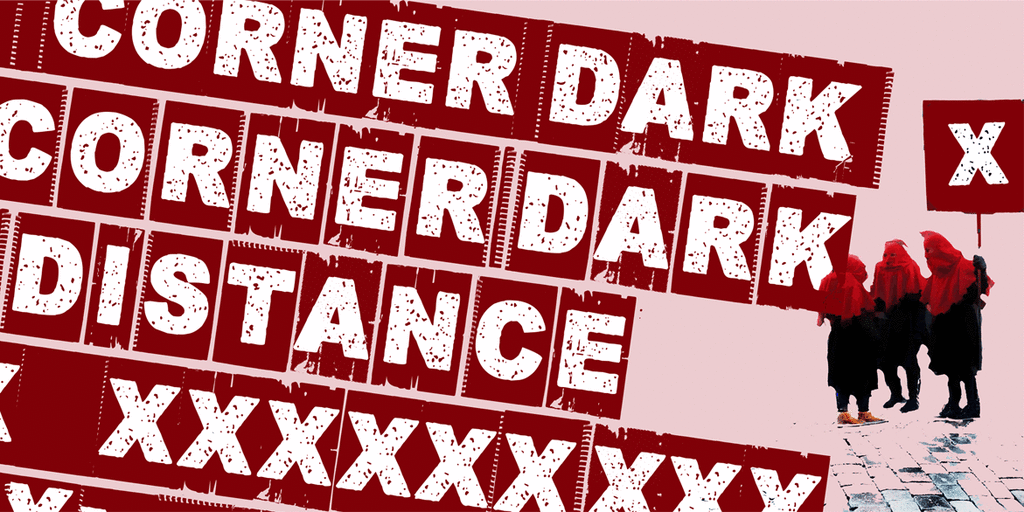
A Fonte Corner Dark é uma família única de fontes decorativas criada pelo designer Hamilton. Essa família de fontes oferece um estilo único que se destaca no ambiente digital, proporcionando um toque especial aos projetos digitais e impressos. Com seu design elegante e sofisticado, a Corner Dark está ideal para adicionar um toque diferenciado em elementos gráficos como nomes de produtos, logotipos ou banners de web. Se você procura uma fonte que destaca-se na tela do computador ou no papel, esta é certamente uma opção. A Hamilton oferece seu trabalho de forma transparente e amigável: as fontes são gratuitas para uso pessoal, mas para uso comercial, como por exemplo em projetos publicitários ou impressão, pode ser necessário adquirir um licença. Para isso, o designer solicita uma contribuição mensal de 15€ (em Euros) ou $20 (Dólares), através do PayPal. Mas não se preocupe, a Hamilton também recebe donativos regulares de seus seguidores e apreciadores da arte da grafia. Essa flexibilidade em termos de pagamento reflete sua atitude aberta e dedicada à comunidade criativa, valorizando o trabalho feito com tanto amor e cuidado. Se você está procurando por uma fonte única para aquele projeto especial, a Corner Dark pode ser exatamente o que você precisa. E, não se esqueça, os contribuintes regulares são sempre bem-vindos!